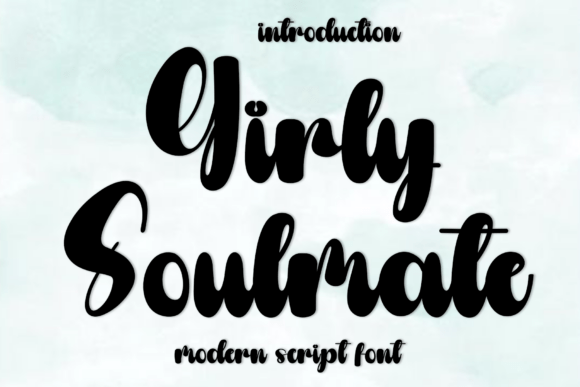
Girly Soulmate
Encontrar los elementos de diseño adecuados puede ser un desafío, pero Girly Soulmate ofrece una colección excepcional que eleva tu trabajo al instante.